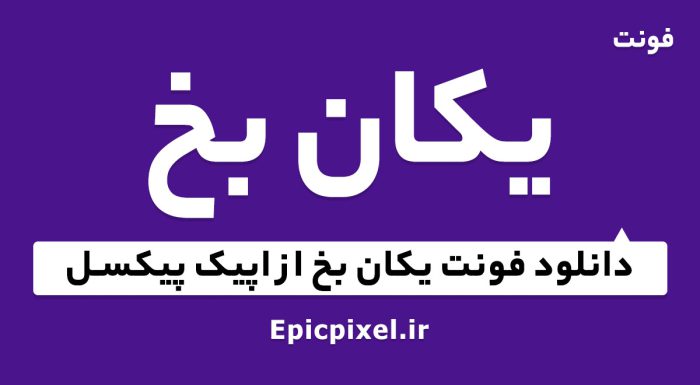
| ⭐ توضیحات | فونت یکان بخ، انتخابی ایده آل برای طراحان و گرافیست هایی است که به دنبال خلق آثار چشم نواز هستند. سادگی، خوانایی، ظرافت و زیبایی این فونت، آن را به ابزاری قدرتمند برای خلق ایده های خلاقانه تبدیل کرده است. در این مقاله، رازهای پنهان در دنیای تایپوگرافی با فونت یکان بخ را به شما خواهیم گفت.
مجموعه ای کامل از فونت های یکان بخ و نسخه شبیه سازی شده بنام اپیک یکان باخ فونت اپیک یخ با پشتیبانی از حروف فارسی ، انگلیسی / لاتین ، اعداد فارسی Fu Num و نسخه وبسایت و نسخه متغییر اپیک یگان بخ |
رازهای پنهان در دنیای تایپوگرافی: دانلود و درخشش با فونت زیبای یکان بخ
آیا تا به حال احساس کرده اید که متون شما در وب یا طرح های گرافیکی تان آن درخشش و گیرایی لازم را ندارند؟ خب، شاید مشکل از انتخاب فونت باشد! در دنیای وسیع فونت های فارسی، فونت یکان بخ همچون الماسی می درخشد و می تواند به شما در خلق آثار چشم نواز یاری رساند. در این مقاله، به همراه هم سفری به دنیای این فونت خاص خواهیم داشت و تمام نکات مربوط به دانلود و استفاده از آن را خواهیم آموخت. پس، همراه ما باشید!
معرفی اجمالی فونت یکان بخ: چرا این فونت را انتخاب کنیم؟
فونت یکان بخ، فرزند خلف فونت خوش نام یکان است. این فونت با ظاهری ساده، خوانا و در عین حال امروزی، برای طیف وسیعی از پروژه های طراحی مناسب است. طراح فونت یکان بخ با وسواس و دقت مثال زدنی، فرم های هندسی را در طراحی حروف به کار گرفته است، به گونه ای که خوانایی و زیبایی بصری فونت حفظ شود.
از جمله ویژگی های بارز فونت یکان بخ می توان به موارد زیر اشاره کرد:
- سادگی و خوانایی: این فونت به خوبی در اندازه های مختلف خوانده می شود و چشمان را خسته نمی کند.
- قابل انعطاف: مناسب برای استفاده در طراحی وب، لوگو، بروشور، پوستر و …
- ظاهری امروزی: با انتخاب این فونت، به طرح های خود جلوه ای مدرن و به روز خواهید بخشید.
فراتر از زیبایی: نکات کلیدی برای استفاده حرفه ای از فونت یکان بخ
با اینکه فونت یکان بخ زیبا و خواناست، اما برای دستیابی به نتایج خیره کننده، رعایت برخی نکات ضروری است:
- انتخاب وزن مناسب: فونت یکان بخ در وزن های مختلفی ارائه می شود. برای متن های اصلی، از وزن های معمولی و برای عناوین، از وزن های بولد استفاده کنید.
- توجه به فضا: فونت یکان بخ را با فونت های مکمل مناسب ست کنید تا خوانایی و زیبایی طرح حفظ شود.
- رعایت سلسله مراتب بصری: با سایز و وزن فونت، بخش های مهم طرح را برجسته کنید.
با کمی تمرین و خلاقیت، می توانید از فونت یکان بخ همچون ابزاری قدرتمند در خلق آثار هنری و گرافیکی بهره مند شوید.
غوطه ور در دنیای یکان بخ: بررسی دقیق تر ویژگی ها
فونت یکان بخ، علاوه بر سادگی و خوانایی، از ظرافت و زیبایی خاصی نیز برخوردار است. طراح این فونت، با دقت و ظرافت فراوان، تناسبات حروف را رعایت کرده است به گونه ای که چشم بیننده را به خود خیره می کند.
دانلوداز دیگر ویژگی های بارز این فونت می توان به موارد زیر اشاره کرد:
- فرم های هندسی جذاب: حروف این فونت از فرم های هندسی ساده و در عین حال ظریف و زیبا تشکیل شده اند.
- تعادل بصری: ارتفاع، ضخامت و فضای بین حروف به گونه ای تنظیم شده است که تعادل بصری را در متن ایجاد می کند.
- حروف فارسی اصیل: طراح این فونت با الهام از خطوط نستعلیق و شکسته، حروفی اصیل و ایرانی خلق کرده است.
- قابلیت ترکیب با فونت های لاتین: فونت یکان بخ به خوبی با فونت های لاتین رایج مانند فونت Arial و فونت Times New Roman ترکیب می شود.
خلاقیت بی حد و مرز: ایده هایی برای استفاده از فونت یکان بخ
با وجود تنوع فونت های موجود، فونت یکان بخ به دلیل ویژگی های منحصر به فرد خود، می تواند انتخابی ایده آل برای طراحان و گرافیست ها باشد. در ادامه، به چند نمونه از ایده های خلاقانه برای استفاده از این فونت اشاره می کنیم:
- طراحی لوگو: فونت یکان بخ به دلیل سادگی و خوانایی، برای طراحی لوگوهای مدرن و امروزی بسیار مناسب است.
- طراحی پوستر و بروشور: با استفاده از این فونت می توانید پوسترهایی چشم نواز و بروشورهایی جذاب طراحی کنید.
- طراحی وب سایت: فونت یکان بخ برای استفاده در طراحی وب سایت های فارسی، به خصوص وب سایت های خبری و آموزشی، ایده آل است.
- طراحی بسته بندی: با استفاده از این فونت می توانید بسته بندی های جذاب و متمایزی برای محصولات خود طراحی کنید.
- طراحی تایتراژ فیلم و سریال: فونت یکان بخ به دلیل ظرافت و زیبایی، برای طراحی تایتراژ فیلم و سریال نیز مناسب است.
جمع بندی: درخشش در دنیای تایپوگرافی با فونت یکان بخ
فونت یکان بخ، انتخابی ایده آل برای طراحان و گرافیست هایی است که به دنبال خلق آثار زیبا و چشم نواز هستند. سادگی، خوانایی، ظرافت و زیبایی این فونت، آن را به ابزاری قدرتمند برای خلق ایده های خلاقانه تبدیل کرده است. با دانلود و استفاده از این فونت، می توانید به دنیای تایپوگرافی درخشش بیافزایید.